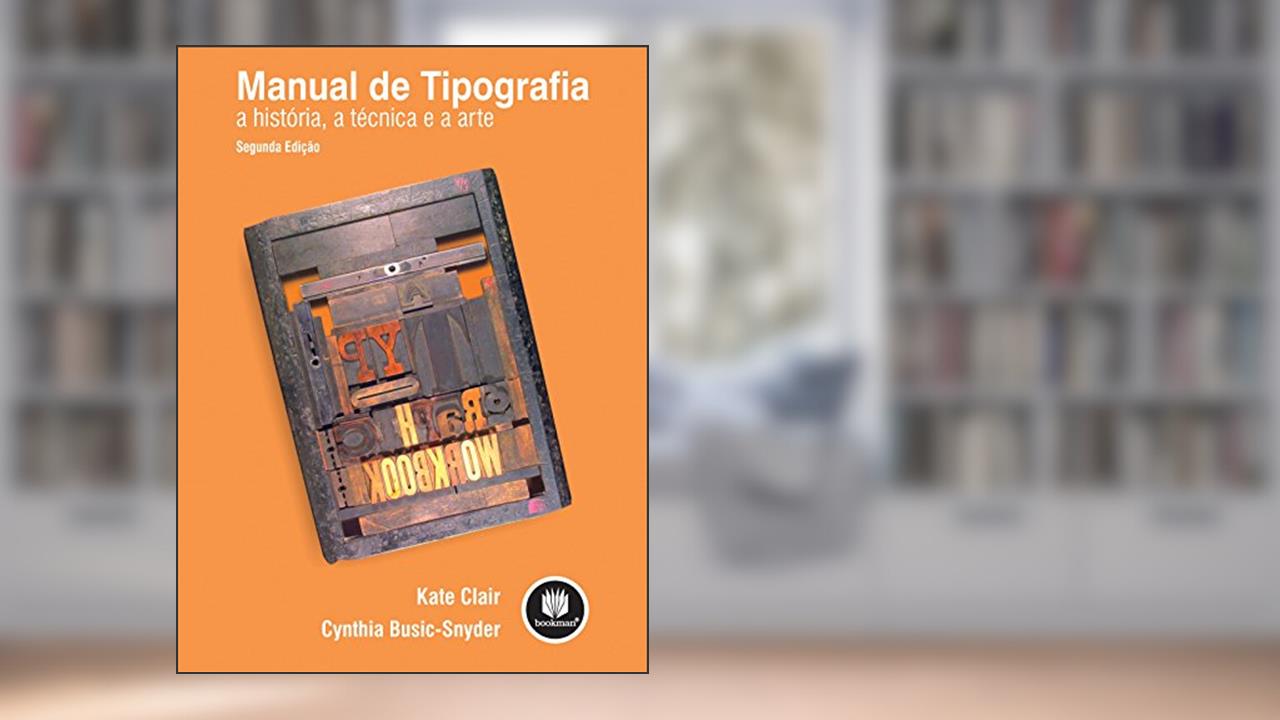
A tipografia, muitas vezes considerada uma arte invisível, desempenha um papel fundamental na construção da nossa comunicação visual. Manual de Tipografia: A História, a Técnica e a Arte não é apenas um compêndio de informações; é um convite a mergulhar na essência do que torna a escrita uma experiência estética e funcional. Este livro, sob a pena de Kate Clair e Cynthia Busic-Snyder, revela um universo onde cada letra é um elemento de uma sinfonia visual, evocando emoções, reflexões e, muitas vezes, uma profunda admiração.
Desde o surgimento da escrita até a era digital, a tipografia evoluiu de maneiras que transcendem simples caracteres. Os autores dedicam suas páginas a explorar essa fascinante jornada, apresentando não apenas a história dos tipos, mas o impacto que eles tiveram e continuam a ter nas nossas vidas. Não é à toa que muitos designers e artistas citam essas letras como suas maiores inspirações. Você já parou para pensar na força de uma fonte específica? Como ela pode, de forma sutil, moldar sua percepção e até mesmo sua emoção? Isso é poder tipográfico!
Os comentários de leitores, em sua maioria, revelam a admiração pela profundidade e rigor da pesquisa apresentada. Há um eloquentemente descrito um "desejo ardente" de compreender que a tipografia é mais do que estética; é uma forma de comunicação que molda ideias e provoca sentimentos. No entanto, como em qualquer obra, há críticas. Alguns acham que o conteúdo pode parecer excessivamente técnico, mas, convenhamos, a tipografia é uma ciência que merece ser desbravada com atenção. É a magia que une a arte à técnica, um passo que não deve ser dado sem reflexão.
Esse livro não é apenas para designers; é uma leitura essencial para qualquer pessoa que se preocupa com a comunicação e a forma como as informações são transmitidas. Ele nos ensina que cada letra, cada espaço, cada altura e espessura se entrelaçam em uma narrativa maior. Este tempo de revolução digital, onde as palavras dançam em telas e impressões, pede uma nova apreciação por essa arte que está nas nossas mãos. A tipografia, afinal, é um reflexo do nosso tempo e das nossas interações.
Desperte para o universo tipográfico e permita que Manual de Tipografia transforme não apenas a forma como você lê, mas como você se comunica e expressa ideias. A jornada é rica e envolvente; não se surpreenda se, ao final, você estiver desejando se aventurar pelo design gráfico ou simplesmente admirando a beleza das letras ao seu redor. O convite de Clair e Busic-Snyder é imperdível, e as lições que você encontrará aqui podem mudar a maneira como você vê o mundo-uma letra de cada vez. 🤔📐✨️